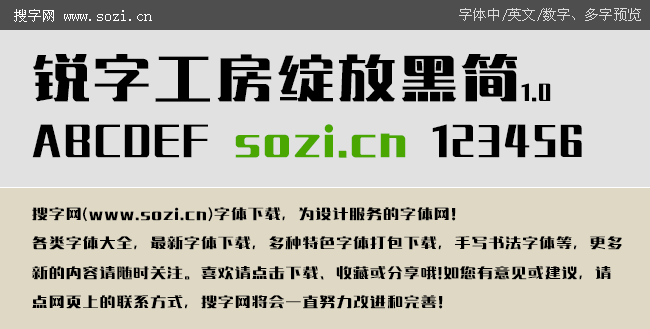
銳字工房綻放黑簡(jiǎn)
搜字網(wǎng)提供一款非常藝術(shù)的黑體銳字工房綻放黑簡(jiǎn)下載,銳字工房綻放黑簡(jiǎn)是一款銳字工房出品的藝術(shù)字體,該字體極具藝術(shù)感,簡(jiǎn)潔大方,適用于包裝印刷、廣告設(shè)計(jì)、平面設(shè)計(jì)、書(shū)籍報(bào)紙等領(lǐng)域。